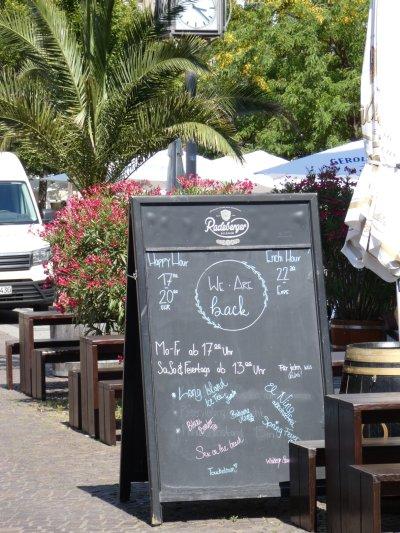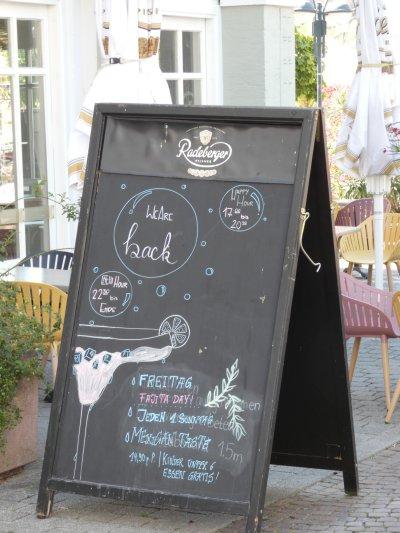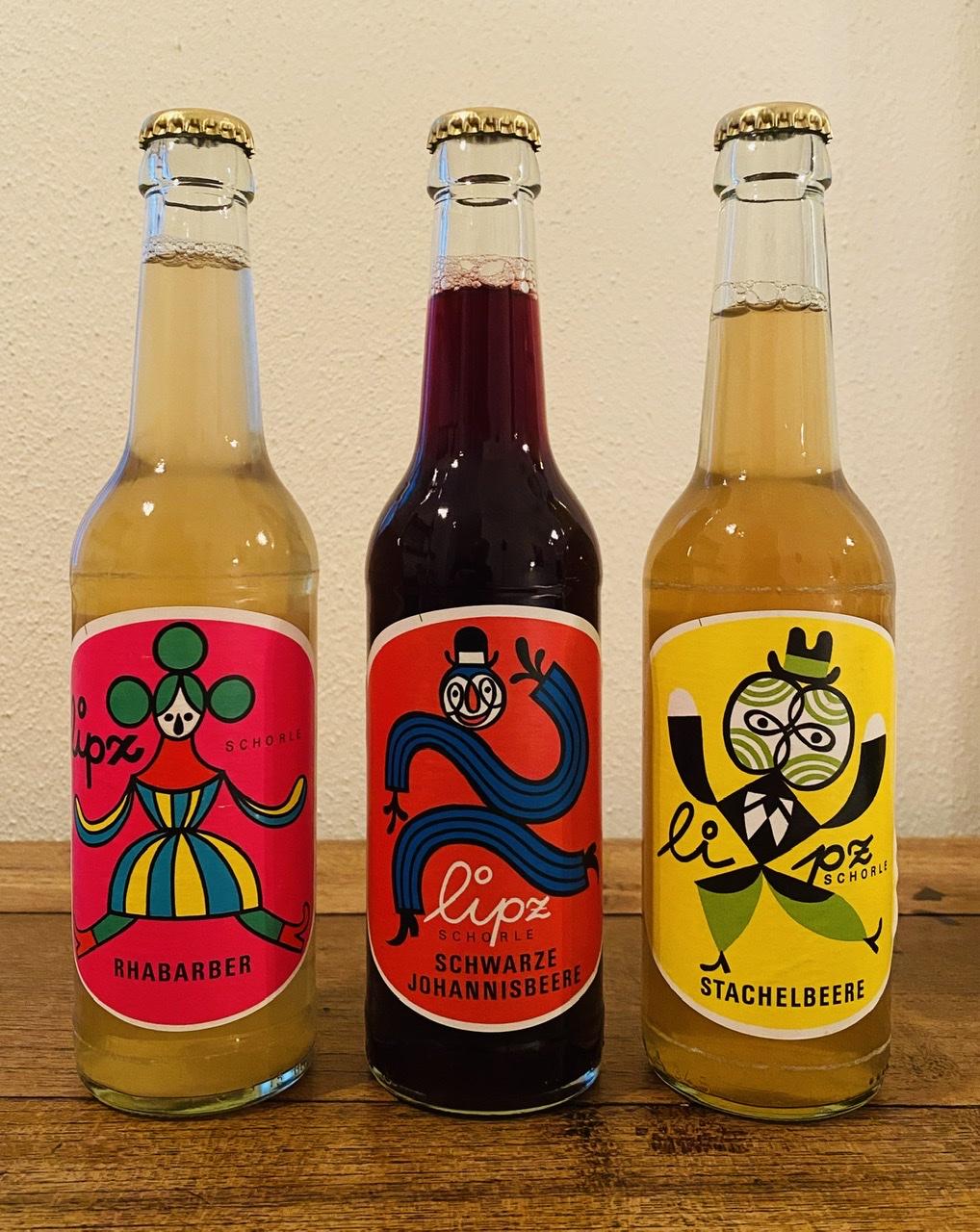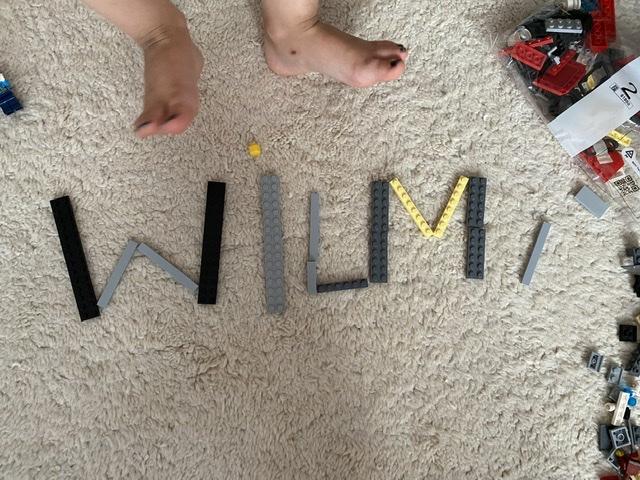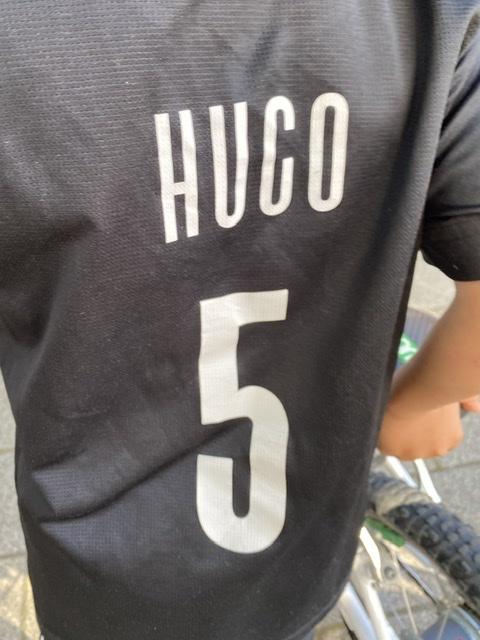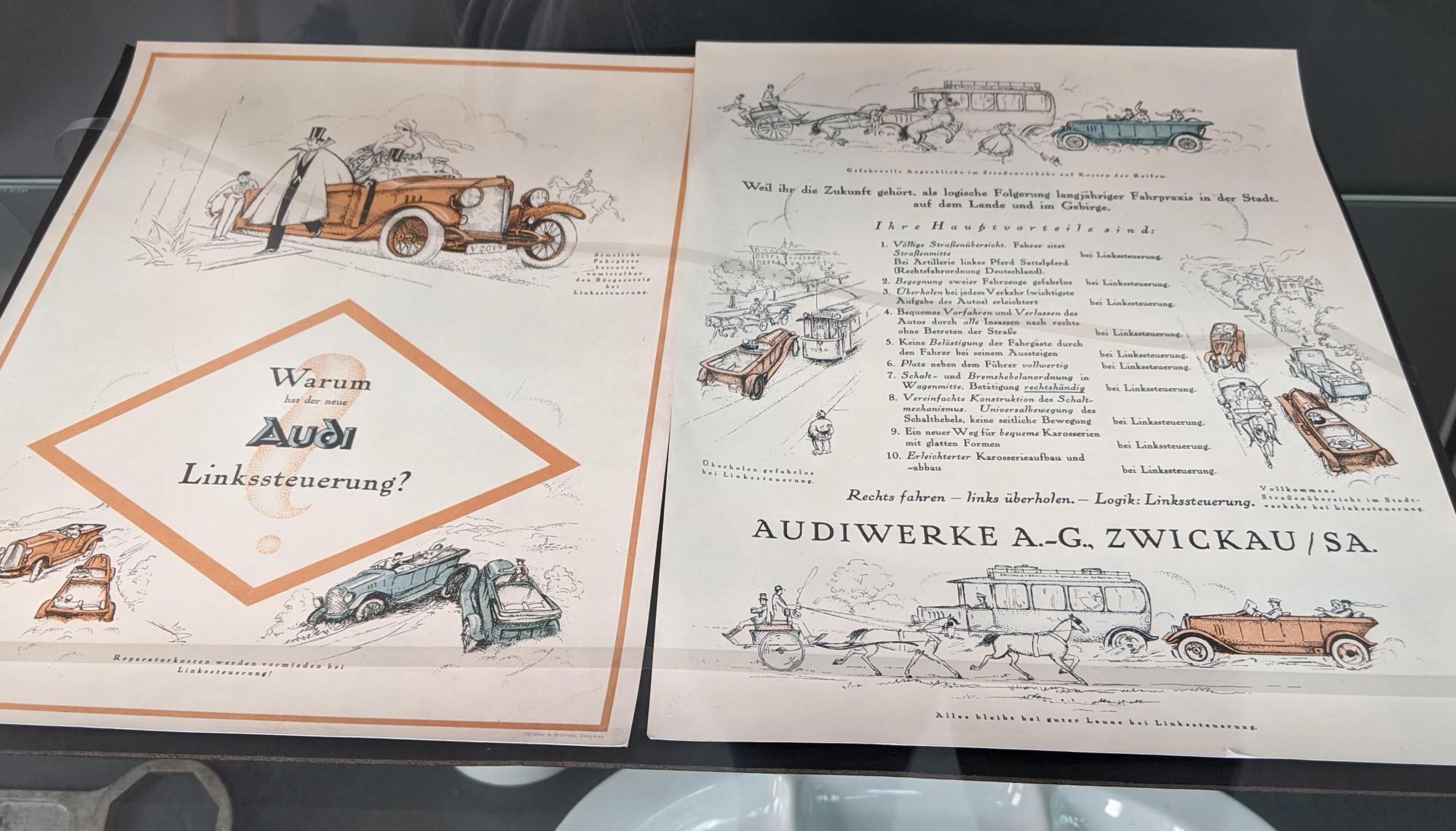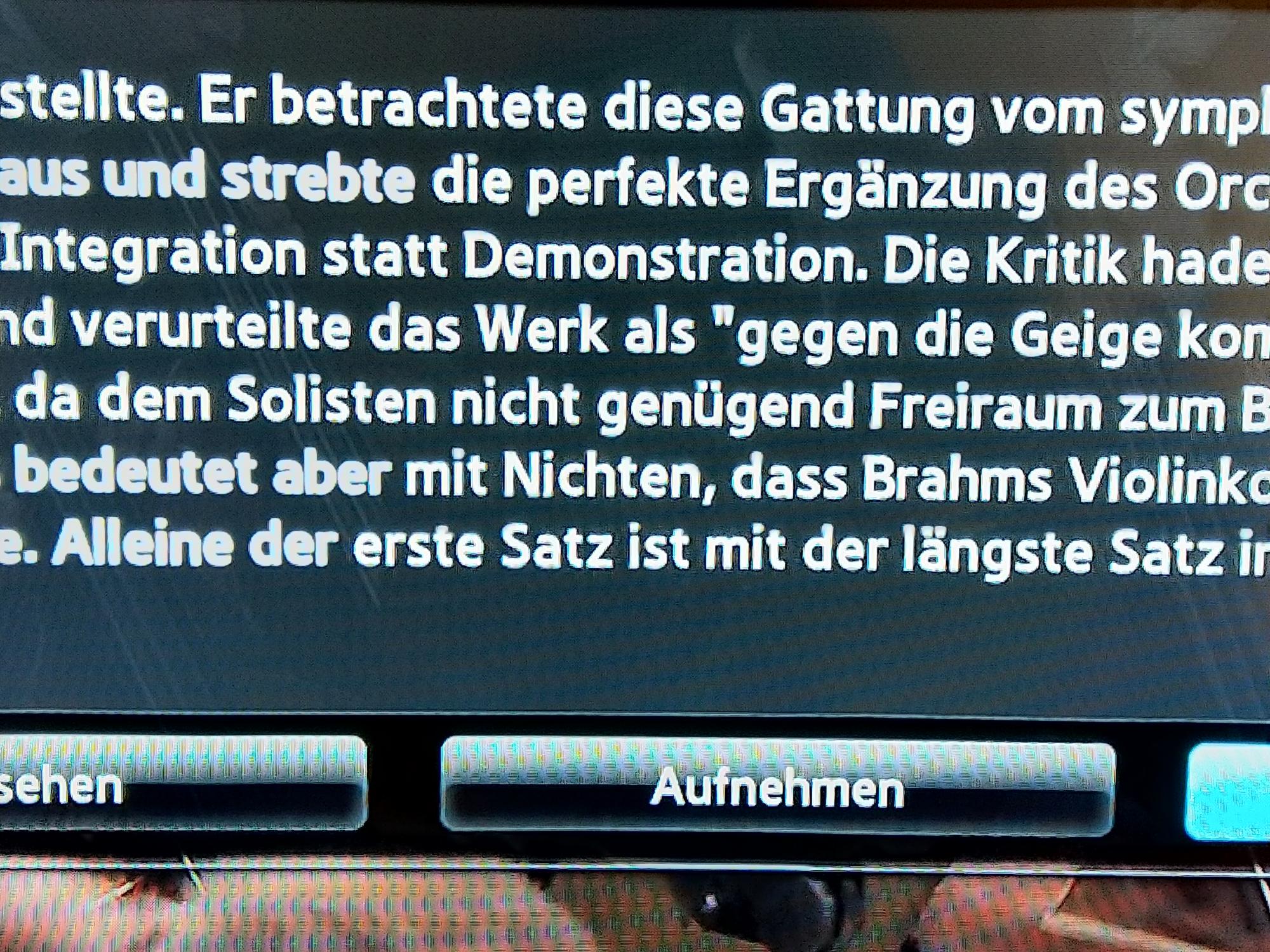
Leergetrunken, jetzt hab ich Angst …
Ich hab am Samstag ausnahmsweise mal Schorle in Flaschen erworben — weil die Etiketten so hübsch waren.
Ich habe drei oder vier Blicke benötigt, um das Cocktailglas als solches zu erkennen. Mein Gehirn hat auf Anhieb nur innere weibliche Geschlechtsorgane erkannt.
Auf dem Rückenfoto lese ich nur »HUCO 5« und sonst nichts. Aber bevor ich mich mit der Erkenntnis zufrieden gegeben habe, dass mir die Fantasie fehlt, habe ich einen Beitrag weiter nach oben gescrollt und siehe da: Das Cocktailglas habe ich sofort erkannt.
So weit runter bis zum Glas bin ich noch gar nicht gekommen, weil ich immer am b/h hängen bleibe ... ;-)
Ich meinte doch ausschließlich *hüstel* das b/h-Verwechselungsproblem in meinen Bildern!!!111😇
Wo ist das ? Enchi ... lada? Irgendwas mimikri-mexikanisches? Wurde an der Uhr am Ludwigsplatz das Ludwigsplatz abmoniert?
Oh, muss ich mal drauf achten ...
Ja, ist das Krokodil, äh, oder so ...
Gerade für Schweizer ist das doch unaussprechlich ohne Knoten im Hals, odrrr
Das ältere Kind (5 Jahre und nicht im Bild) hat beim spielen mit Lego seinen Spitznamen »gebaut« – schreiben bzw. malen konnte sie ihn schon.
Ich hab da ein k gelesen, b/h konnte ich nicht entdecken.